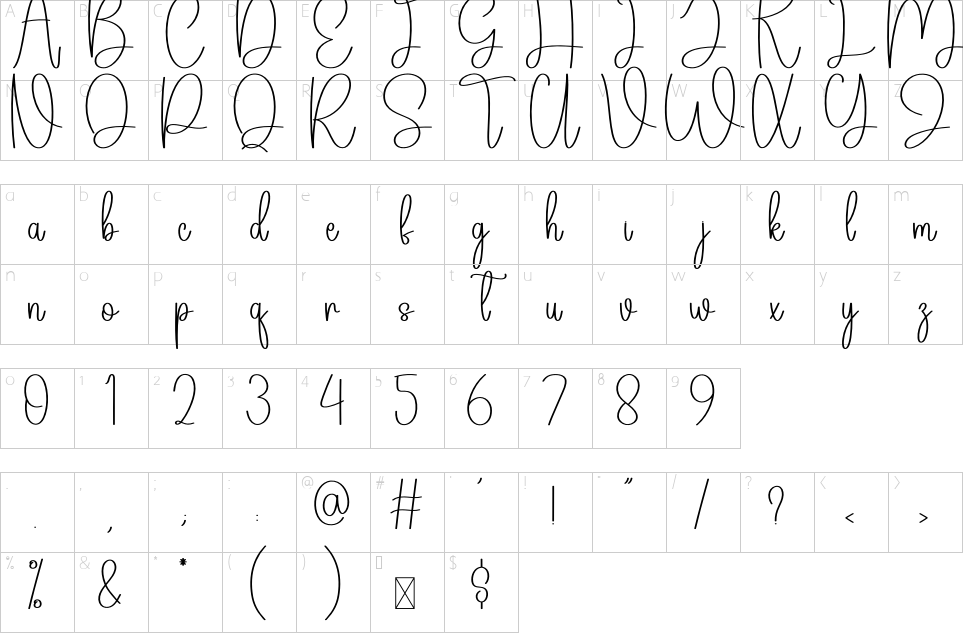
Audiography Font
Audiography é uma elegante fonte gráfica que oferece um toque moderno e sofisticado para qualquer projeto. Desenvolvida por scratchones, esta fonte já foi baixada mais de 550 vezes. Ela traz uma sensação de conforto e modernidade ao seu trabalho, seja em títulos ou textos. Seja para criações web, design gráfico ou até mesmo para projetos de impressão, a Audiography traz uma qualidade de impressão impecável. Suavemente elegante e versátil, esta fonte é certamente uma escolha atraente para quem busca uma fonte única e de alta qualidade para seus projetos. Em uma categoria de fontes gratuitas, Audiography é uma escolha inteligente para quem procura uma opção de fontes de alta qualidade sem precisar pagar.
Mapa de caracteres da fonte Audiography Font